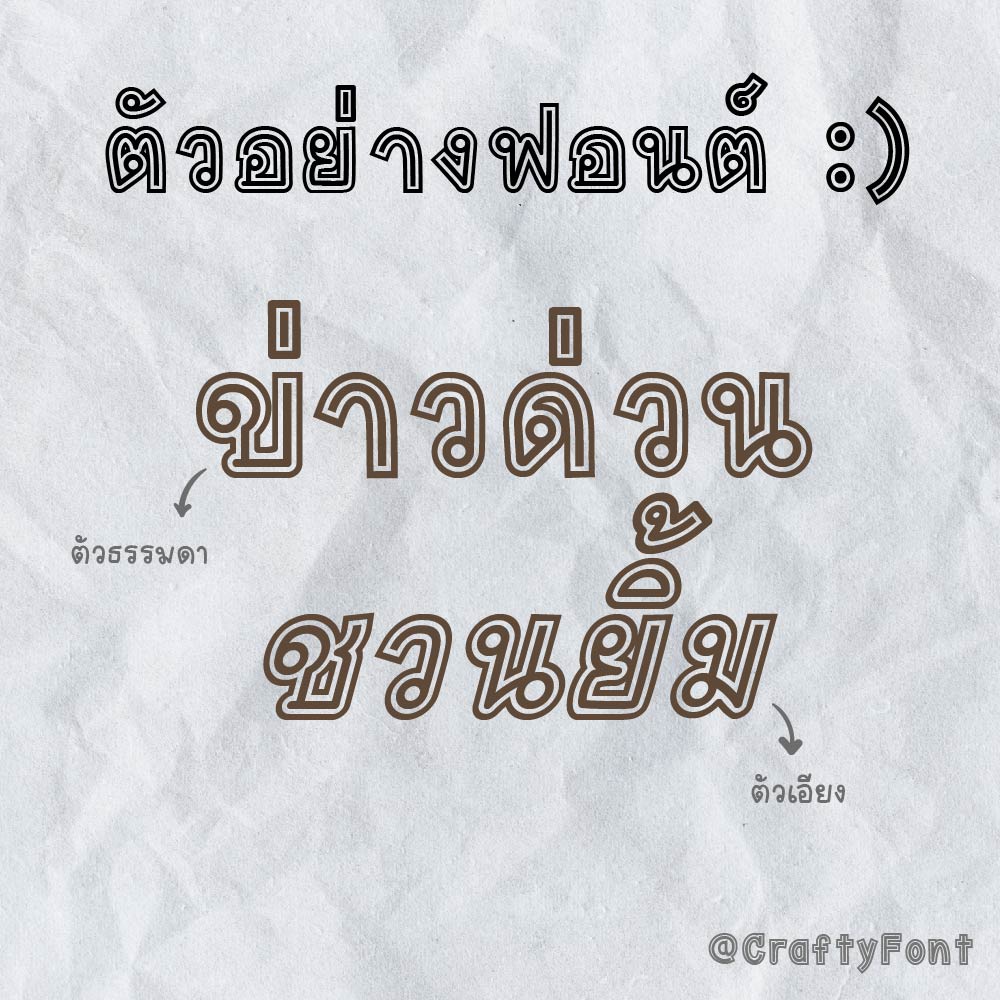
ชื่อฟอนต์ : แคปซูล
ฟอนต์ทรงแคปซูล ตัวแรกสูงกว่าใคร ..แค่นั้นเลย
ชื่อฟอนต์ : ม้วนหัว
จะเรียกว่า..ต้นแบบมาจากโลโก้แบรนด์ นลินเฟี้ยว ก็ไม่ผิด ดังนั้นฟอนต์ม้วนหัวจึงเป็นแนวโลโก้ฟอนต์ อักษรเด้งๆ เหมาะกับคำสั้นๆ
ชื่อฟอนต์ : ตะเกียบ
ฟอนต์ตะเกียบ แท่งตรงยาวมาเป็นคู่ ยาวเท่ากันแต่ไม่เคยเท่ากัน วางแล้วขนานกันแต่ไม่ขนานกัน เหมือนเป็นระเบียบแต่ไม่เป็นระเบียบ
ฟอนต์ FC Sound Rounded แบบตัวมนของฟอนต์ FC Sound อีกทีฮะ
ฟอนต์ Kidza ฟอนต์วันเด็กค่า
ฟอนต์เอฟซี มัคคิอาโต้ (FC Macchiato)